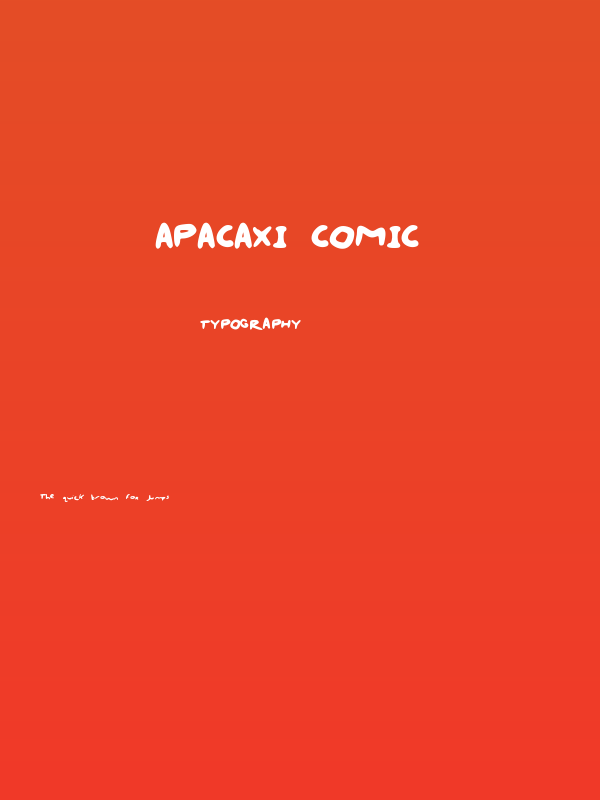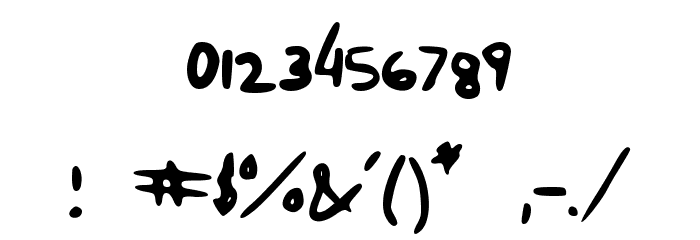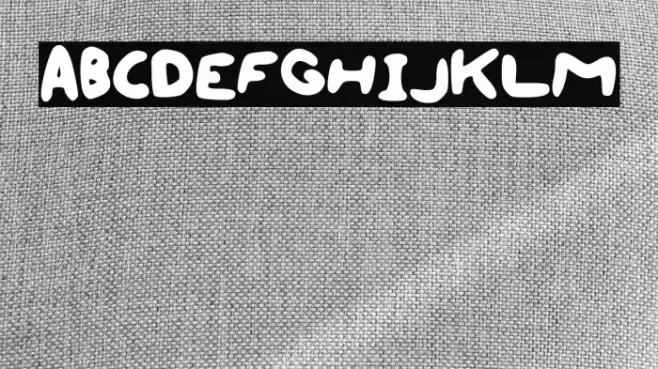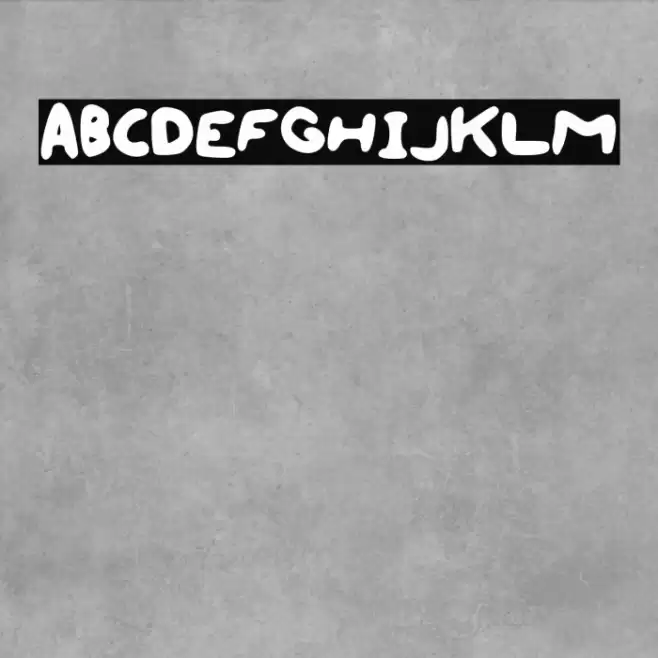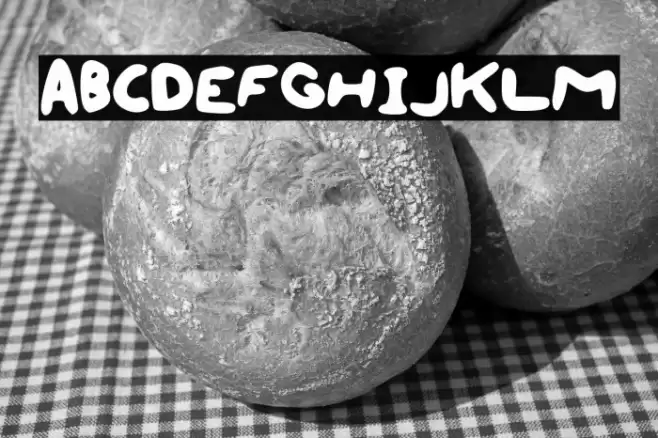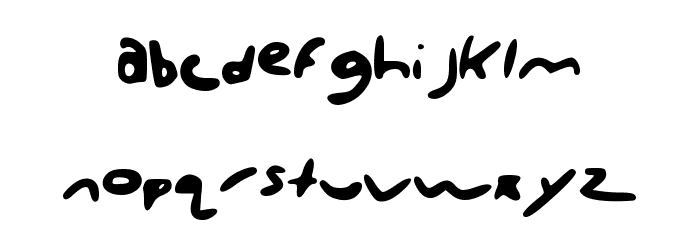
Apacaxi_Comic_ Font
| समग्र शैली | Playful, Comic |
| उपयोग का मामला | Headlines, Logos, Posters |
| सुझाए गए प्रोजेक्ट | Ideal for comic books, children's books, playful branding, posters, and any project requiring a fun, informal touch. |